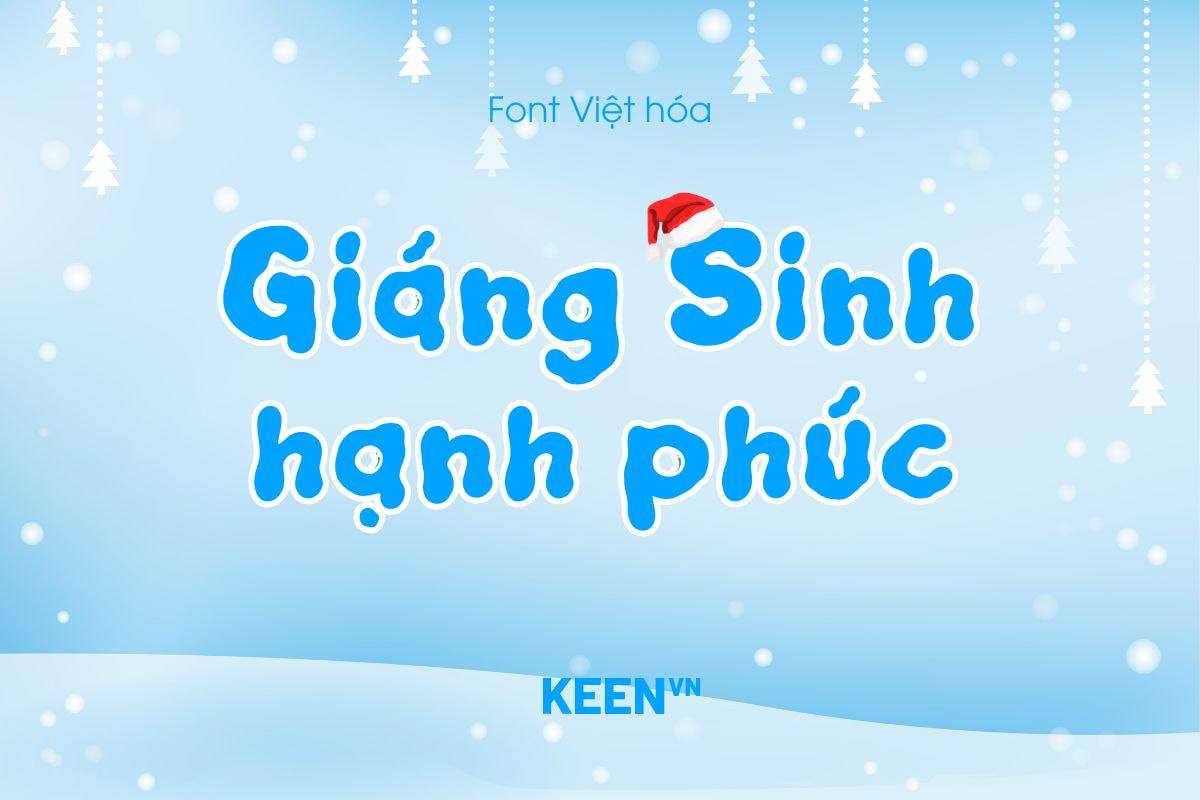
Font Việt hóa TP Sense Egg
Font Việt hóa TP Sense Egg mang đến một làn gió mới cho những ai yêu thích phong cách thiết kế phá cách và sáng tạo. Được phát triển bởi Attype Studio, font chữ này gây ấn tượng ngay từ cái nhìn đầu tiên nhờ các ký tự cong vẹo, dáng chữ tinh nghịch và tinh thần vui tươi rất riêng. Phiên bản Việt hóa do Tuỳn Pucca thực hiện giúp bộ font hỗ trợ trọn vẹn tiếng Việt, mở ra nhiều cơ hội ứng dụng linh hoạt cho cộng đồng thiết kế trong nước. Đây cũng là một trong những font được chia sẻ bởi thành viên của Font Chuẩn, minh chứng cho sự quan tâm và nhu cầu lớn đối với những kiểu chữ độc đáo phục vụ sáng tạo.
Những đường nét không đồng đều của TP Sense Egg tạo ra cảm giác thủ công và mang đậm chất nghệ thuật, khiến mỗi dòng chữ như đang kể một câu chuyện bằng chính hình dáng của nó. Kiểu chữ này đặc biệt phù hợp cho những thiết kế cần nét nhấn mạnh về cá tính như bìa sách, poster sự kiện, tiêu đề hay các sản phẩm quảng cáo mang tinh thần trẻ trung. Với phong cách vui nhộn, phóng khoáng, TP Sense Egg dễ dàng thu hút người xem và tạo cảm giác thân thiện nhưng vẫn táo bạo.
Dành cho những nhà thiết kế muốn tìm kiếm một font chữ có khả năng truyền tải cảm xúc mạnh mẽ, khác biệt hoàn toàn với các kiểu chữ truyền thống, TP Sense Egg chắc chắn là lựa chọn đáng thử. Nó không chỉ là một bộ font, mà còn là chất liệu sáng tạo giúp bạn nâng tầm sản phẩm đồ họa và tạo dấu ấn thị giác độc nhất trong mọi dự án.